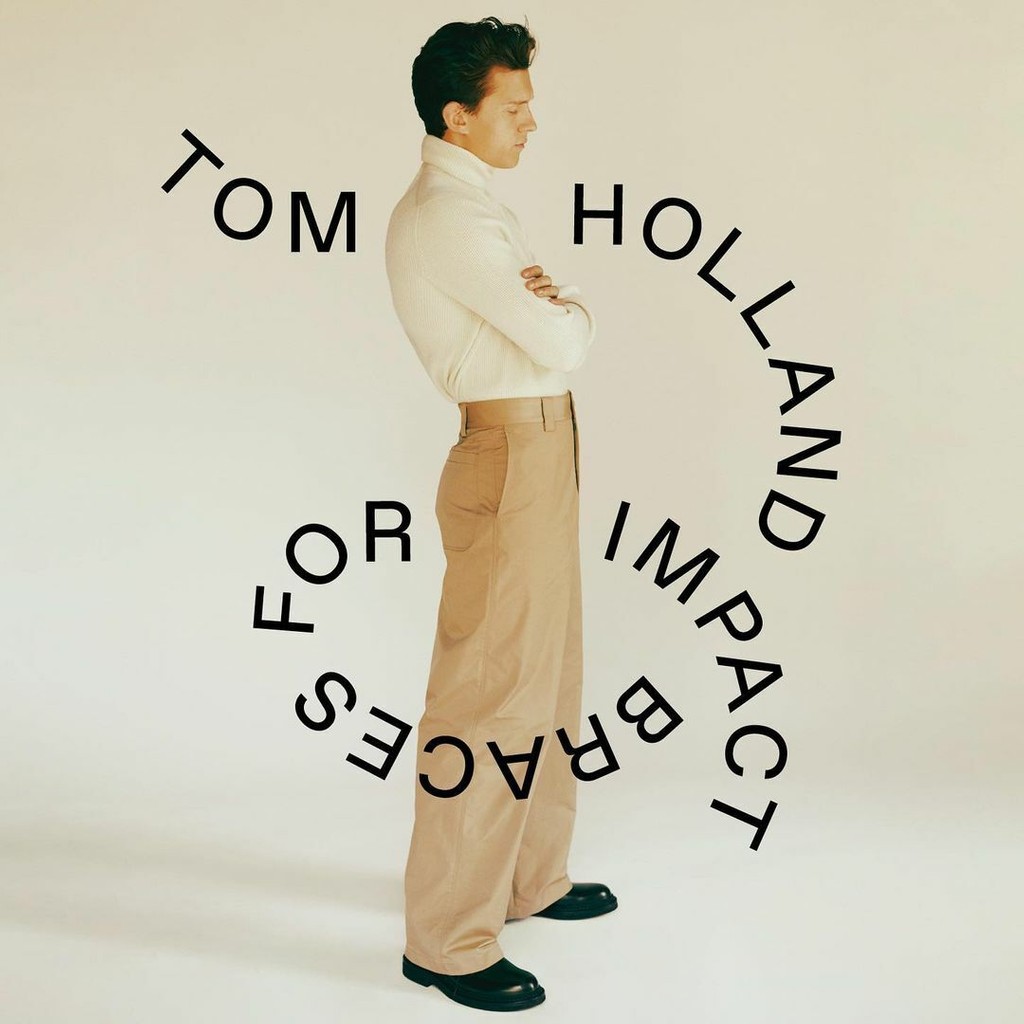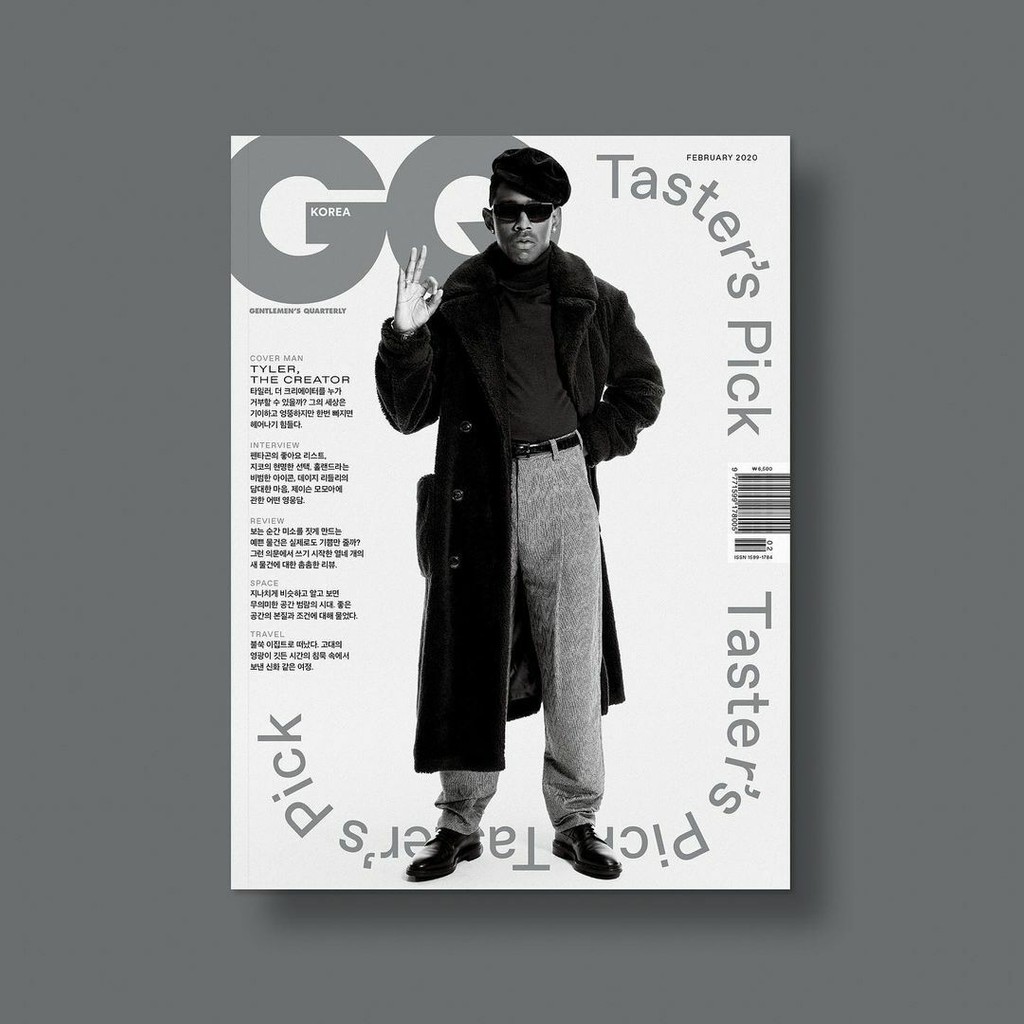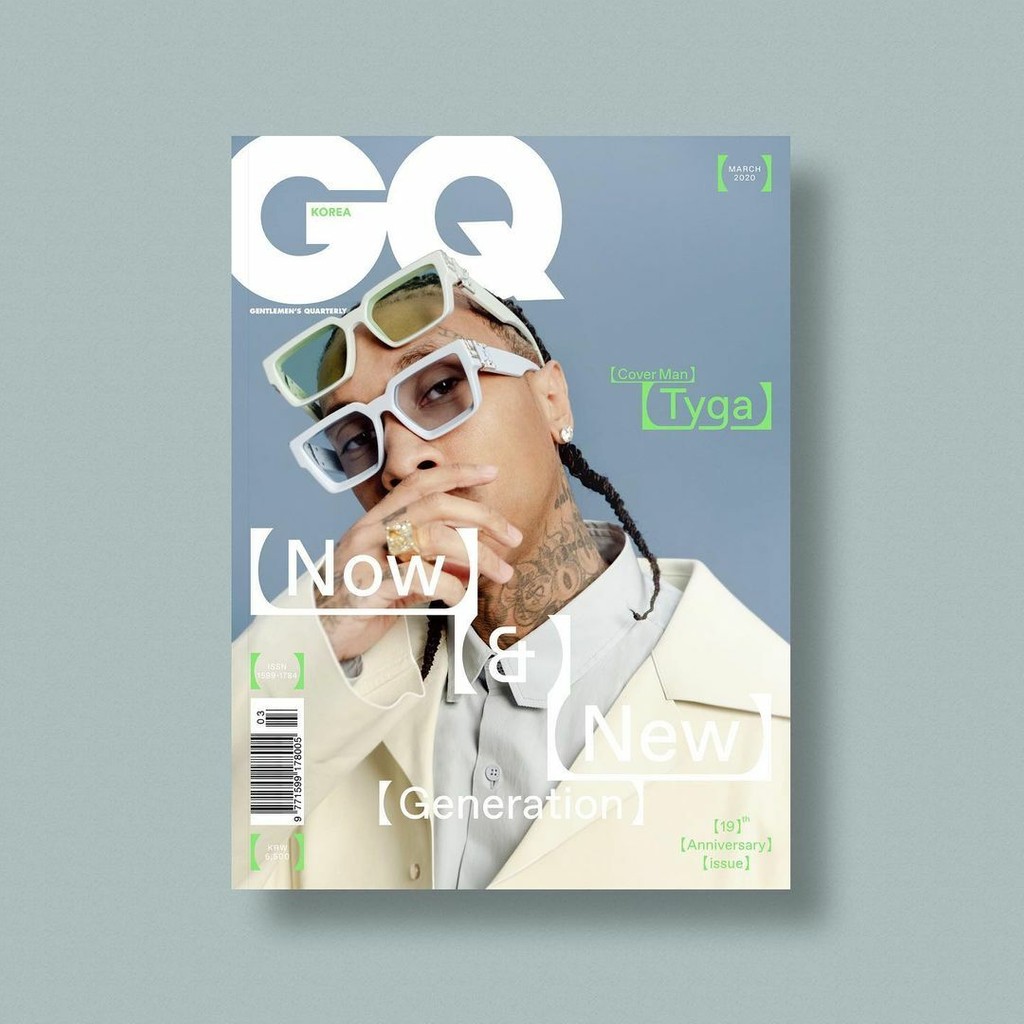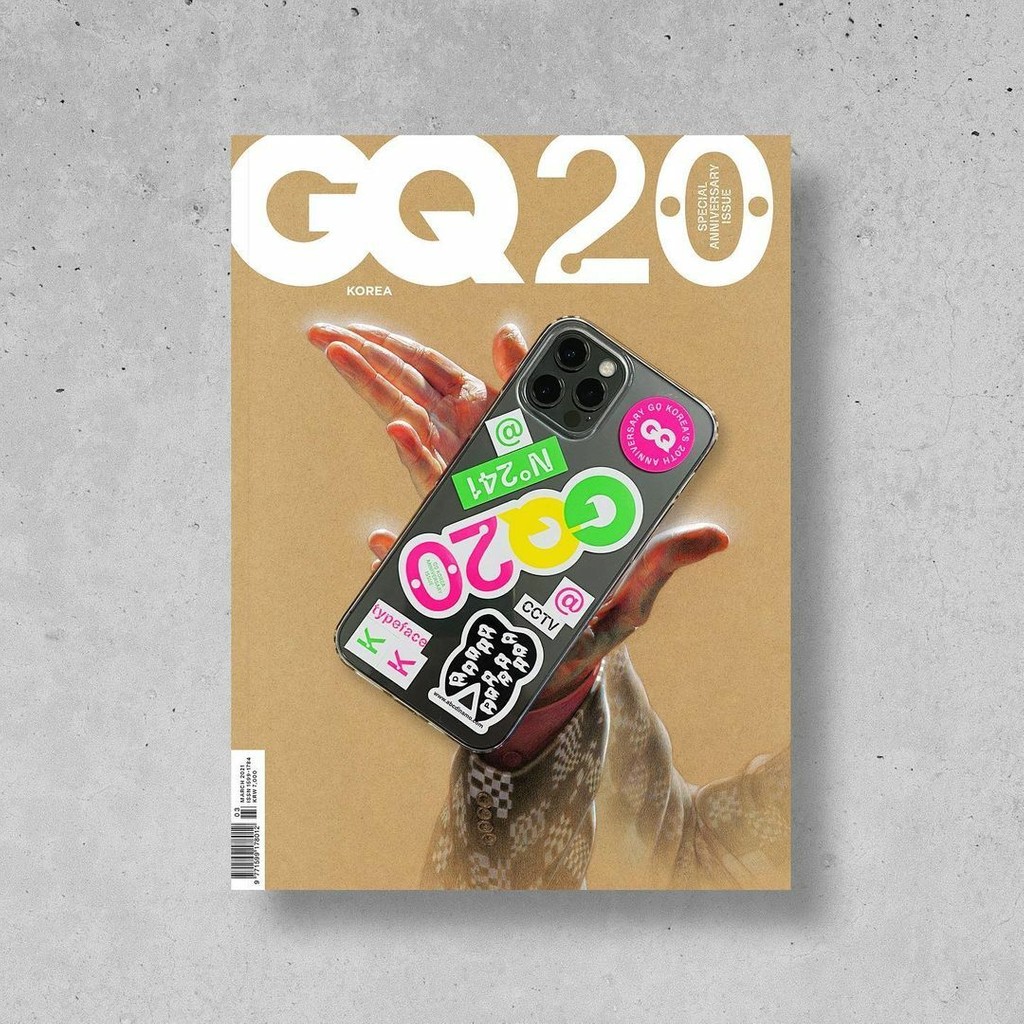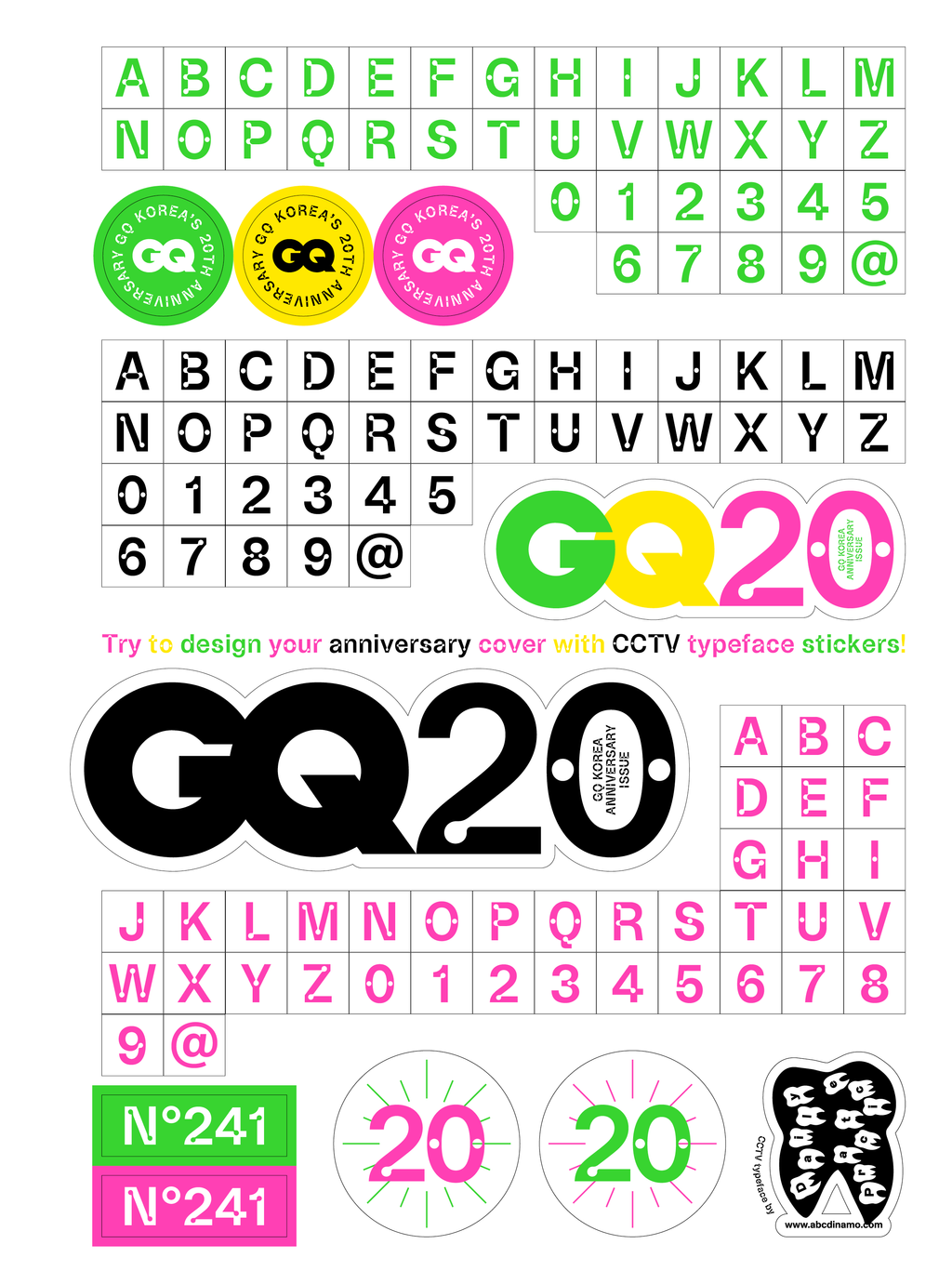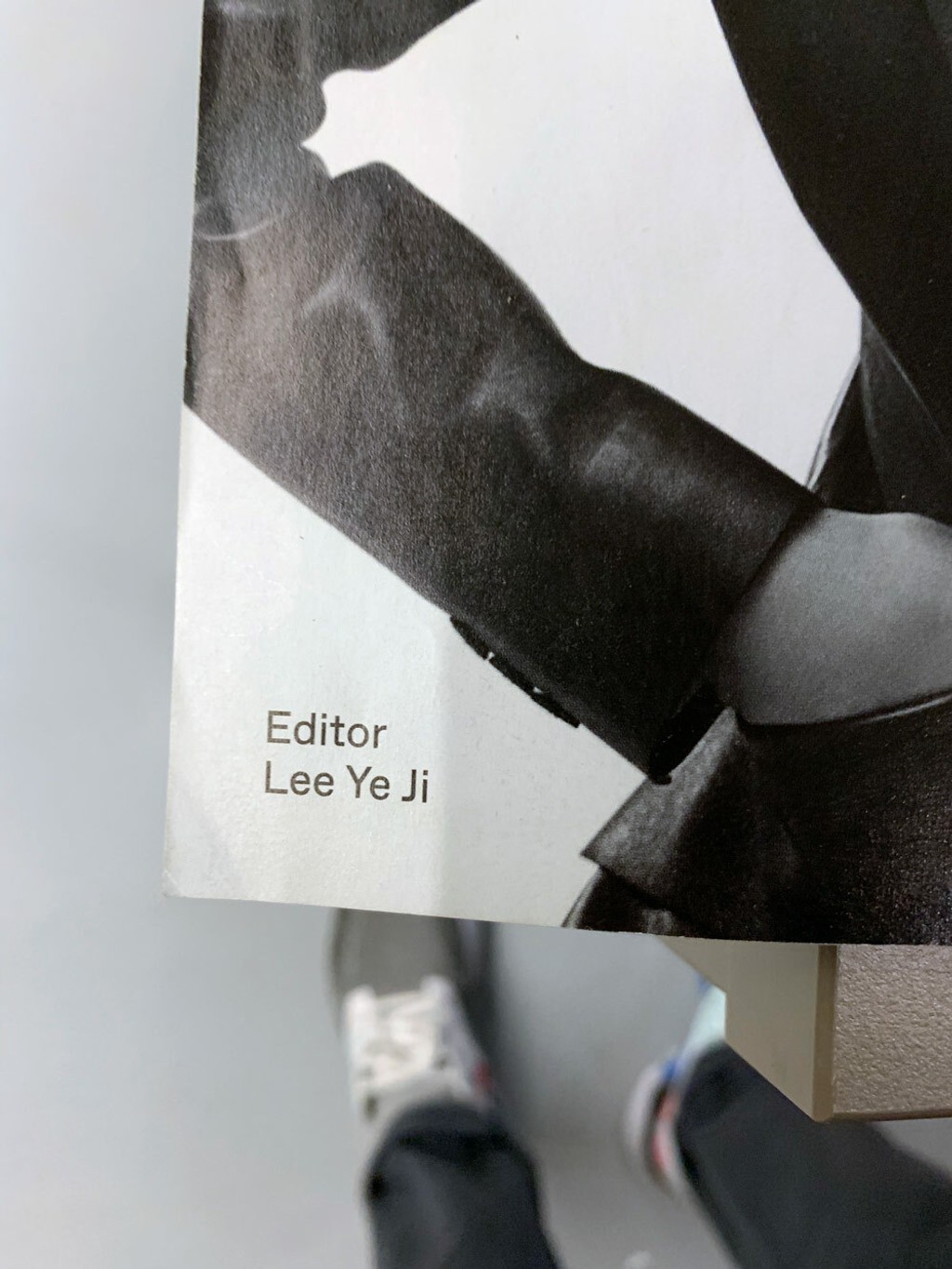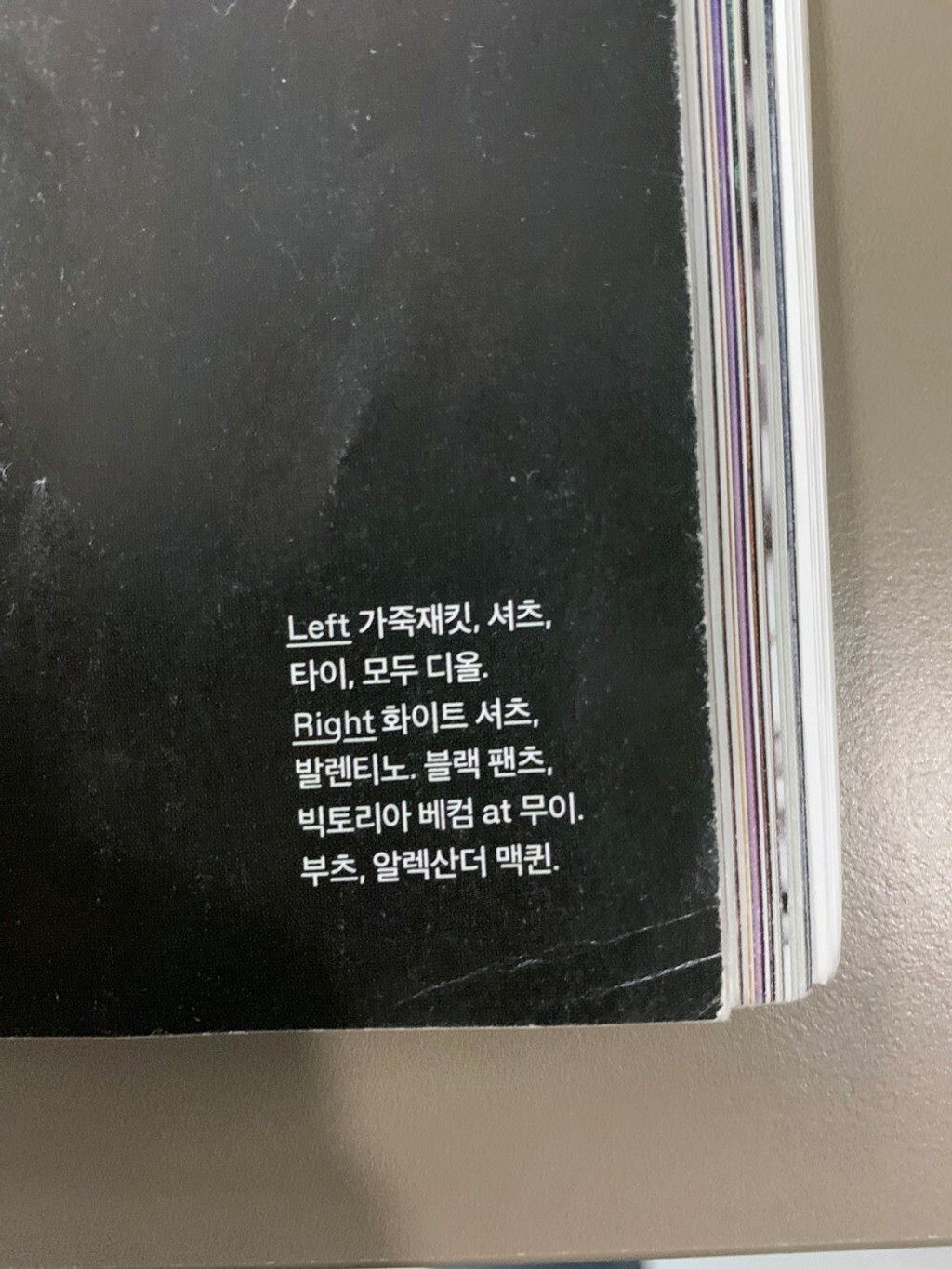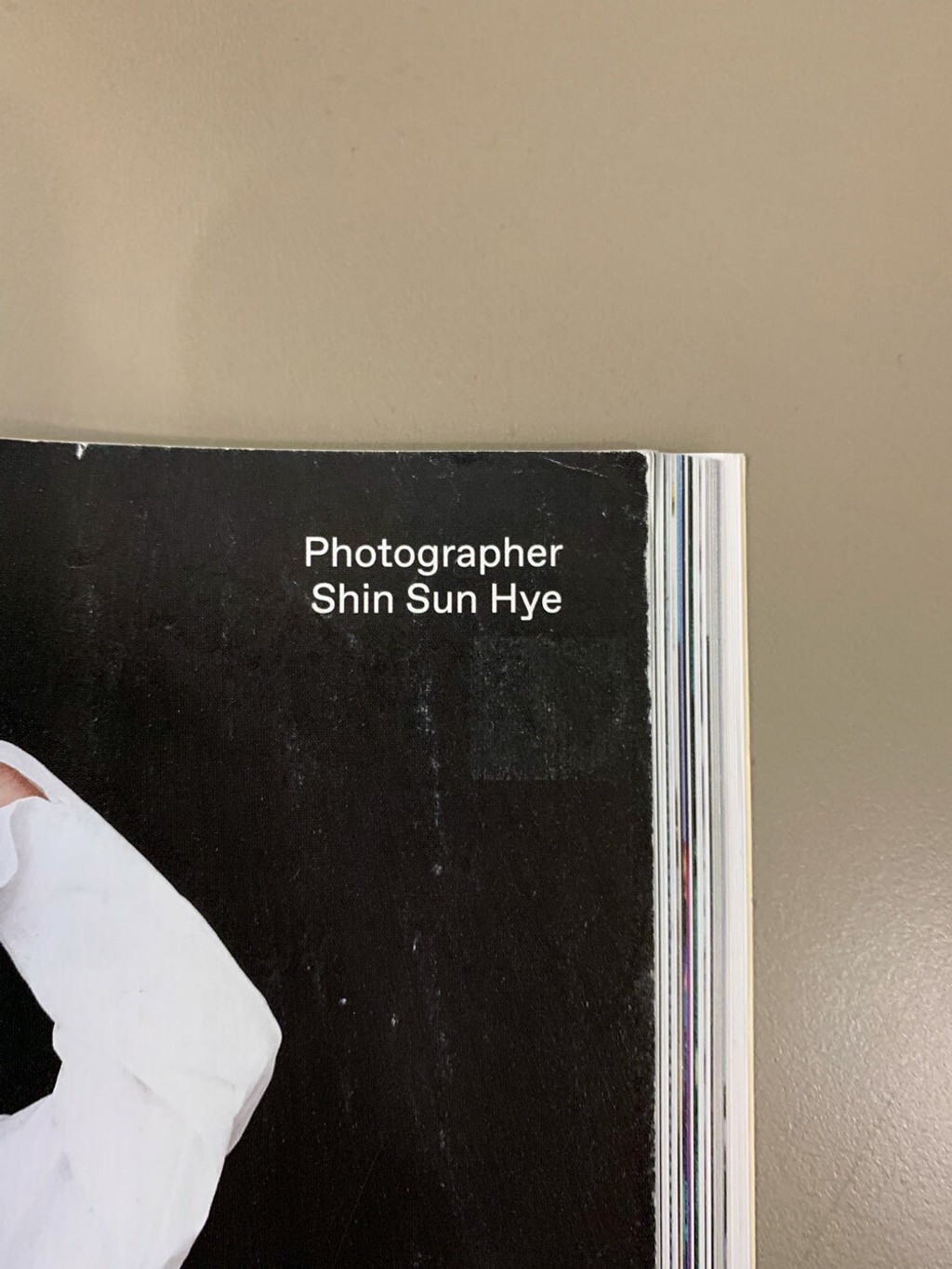
๋””๋‚˜๋ชจ x ๊น€๊ธฐ์—ด (์ง€ํ ์ฝ”๋ฆฌ์•„)
Dinamo x Kiyeol Kim at GQ Korea
์šฐ๋ฆฌ๋Š” ์ˆ˜๋…„๊ฐ„ ๊น€๊ธฐ์—ด๊ณผ ๋ฉ”์‹œ์ง€, โ€˜ํ•˜๋“œ์›จ์–ดโ€™ ๋ฐ ์‚ฌ์ „ ์ถœ์‹œ๋œ ๊ธ€๊ผด ํŒŒ์ผ์„ ๊ตํ™˜ํ•ด์™”๋‹ค. ์ง€ํ ์ฝ”๋ฆฌ์•„์—์„œ ๊น€๊ธฐ์—ด์€ ์ข…์ข… ํ•œ๊ธ€์˜ ํ•ต์‹ฌ๊ณผ ๊ทธ์— ๋Œ€์‘ํ•˜๋Š” ๋ผํ‹ด ํฐํŠธ๋ฅผ ๋ฉ‹์ง€๊ฒŒ ๊ฒฐํ•ฉํ•˜๋Š”๋ฐ, ์šฐ๋ฆฌ๋Š” ์ด ์•„ํŠธ ๋””๋ ‰ํ„ฐ๊ฐ€ ๋””์ž์ธ์— ์ ‘๊ทผํ•˜๋Š” ๋ฐฉ์‹์„ ํ•ญ์ƒ ํฅ๋ฏธ๋กญ๊ฒŒ ์ง€์ผœ๋ด ์™”๋‹ค. ๊ทธ ๋•์— ์šฐ๋ฆฌ๋Š” Camera, Maxi ๊ทธ๋ฆฌ๊ณ  Favorit๊ฐ€ ์ฒ˜์Œ์œผ๋กœ ์žก์ง€์— ๋“ฑ์žฅํ•˜๋Š” ๋ชจ์Šต์„ ์ฆ๊ฑฐ์šด ๋งˆ์Œ์œผ๋กœ ๋ณผ ์ˆ˜ ์žˆ์—ˆ๋‹ค. ์ตœ๊ทผ์—๋Š” ์ง€ํ ์ฝ”๋ฆฌ์•„๋„ ๋””๋‚˜๋ชจ์˜ ์ฒซ ํ•œ๊ธ€ ๊ธ€๊ผด์ธ ํŒŒ๋ณด๋ฆฌํŠธ ํ•œ๊ธ€(Favorit Hangul)์˜ ํŠน๋ณ„ํ•œ ์„œํฌํ„ฐ๊ฐ€ ๋˜์–ด์ฃผ์—ˆ๋‹ค.
February 2020 issue featuring Tasterโ€™s Pickโ€”Tyler the Creator, all typeset in Favorit Hangul.
March 2020 issue celebrating 19 years GQ Korea, and featuring Tyga and Favorit Hangul Lining.
Double spread from the September 2020 issue in Maxi.
2019๋…„ ํƒ€์ดํฌ์ž”์น˜์— ์ฐธ์—ฌํ–ˆ์„ ๋•Œ, ์šฐ๋ฆฌ๋Š” ๋“œ๋””์–ด ๊น€๊ธฐ์—ด๊ณผ ๊ฐœ์ธ์ ์œผ๋กœ ์†Œํ†ตํ•  ๊ธฐํšŒ๋ฅผ ์–ป๊ฒŒ ๋˜์—ˆ๋‹ค. ๊ทธ๊ณณ์—์„œ ์šฐ๋ฆฌ๋Š” ์œค๋ฏผ๊ตฌ๊ฐ€ ๋””์ž์ธํ•œ ํŒŒ๋ณด๋ฆฌํŠธ ํ•œ๊ธ€(Favorit Hangul)์˜ ์ถœ์‹œ๋ฅผ ๊ธฐ๋…ํ•˜์—ฌ ๊น€๋‚˜์š”, ๊ฐ•๋ฌธ์‹๊ณผ ํ•จ๊ป˜ ์ผ๋ จ์˜ โ€˜ํ•˜๋“œ์›จ์–ดโ€™ ์‹œ๋ฆฌ์ฆˆ๋ฅผ ์ œ์ž‘ํ•˜์˜€๋‹ค. ๊ทธ๋•Œ ์ดํ›„๋กœ ์šฐ๋ฆฌ๋Š” ์œค๋ฏผ๊ตฌ์™€ ํ•จ๊ป˜ (์—ฌ์ „ํžˆ ๋ฒ ์ผ์— ๊ฐ€๋ ค์ง„) ์šฐ๋ฆฌ์˜ ๋‘ ๋ฒˆ์งธ ํ•œ๊ธ€ ๊ธ€๊ผด ์ž‘์—…์— ๋ชฐ๋‘ํ•ด์˜ค๊ณ  ์žˆ๋‹ค(์ž์„ธํ•œ ๋‚ด์šฉ์€ ๊ณง). ๋ฐ”์ด ์Šคํฌ๋ฆฝํŠธ ํƒ€์ž… ๋””์ž์ธ์— ๊ด€ํ•ด ์œค๋ฏผ๊ตฌ๋Š” ์ด๋ ‡๊ฒŒ ๋งํ•œ๋‹ค. โ€œ์™„์ „ํžˆ ๋‹ค๋ฅธ ๋ณธ์„ฑ์„ ์ง€๋‹Œ ๋‘ ๊ฐœ์˜ ์Šคํฌ๋ฆฝํŠธ๋ฅผ ์กฐํ™”์‹œํ‚ค๋Š” ์ผ์€ ๊ฝค ๋„์ „์ ์ธ ์ž‘์—…์ด๋‹ค. ๊ฐ€๋ น ํ•œ๊ธ€์€ ๋ฒ ์ด์Šค๋ผ์ธ ๊ธฐ๋ฐ˜์˜ ์„œ์ฒด๊ฐ€ ์•„๋‹ˆ๊ธฐ ๋•Œ๋ฌธ์—, ๋ผํ‹ด๊ณผ ํ•œ๊ธ€ ๊ธ€๊ผด์„ ํ•œ ์ค„๋กœ ์ •๋ ฌํ•˜๋Š” ์ผ์€ ํ•ญ์ƒ ์ฒซ ๋ฒˆ์งธ ๋‹จ๊ณ„๋ผ ํ•  ์ˆ˜ ์žˆ๋‹ค. ํŒŒ๋ณด๋ฆฌํŠธ ํ•œ๊ธ€(Favorit Hangul)์˜ ๊ฒฝ์šฐ, ์„œ์ฒด ์ž์ฒด๋ฟ๋งŒ ์•„๋‹ˆ๋ผ ๋””๋‚˜๋ชจ์˜ ๋…ํŠนํ•˜๊ณ  ์žฌ๋ฏธ์žˆ์œผ๋ฉฐ ๋ฐœ๋ž„ํ•œ ๊ฐœ์„ฑ์„ ํ‘œํ˜„ํ•˜๋Š” ๊ฒƒ์ด ์ฃผ์š” ๊ณผ์ œ์˜€๋‹ค. ๊ฒฐ๊ตญ, ์•„์ฃผ ์ƒˆ๋กญ๊ณ  ์˜ˆ์ƒ์น˜ ๋ชปํ•œ ๊ฒฐ๊ณผ๊ฐ€ ๋‚˜์™”๋Š”๋ฐ, ํ•œํŽธ์œผ๋กœ๋Š” ์œ ๋จธ๋Ÿฌ์Šคํ•˜๋ฉด์„œ๋„ ๋‹ค๋ฅธ ํ•œํŽธ์œผ๋กœ๋Š” ๊ธฐ๋ณธ์— ์ถฉ์‹คํ•œ ๊ฒฐ๊ณผ๋ฌผ์ด๋ผ ํ•  ์ˆ˜ ์žˆ๋‹ค.โ€
๋‹ค๊ฐ€์˜ค๋Š” ๋””๋‚˜๋ชจ ํ•œ๊ธ€ ๊ธ€๊ผด ์ถœ์‹œ๋ฅผ ์•ž๋‘๊ณ (์šฐ๋ฆฌ๊ฐ€ ํ•ญ์ƒ ์–˜๊ธฐํ•ด์™”๊ธฐ ๋•Œ๋ฌธ์—), ์šฐ๋ฆฌ๋Š” ๊น€๊ธฐ์—ด์—๊ฒŒ ํ•œ๊ตญ์˜ ์„œ์ฒด ๋””์ž์ธ๊ณผ ์ง€ํ ์ฝ”๋ฆฌ์•„์— ๊ด€ํ•œ ๊ทธ์˜ ์ „๋ฐ˜์ ์ธ ๋น„์ „์„ ๋“ฃ๊ณ ์ž ๋ช‡ ๊ฐ€์ง€ ์งˆ๋ฌธ์„ ๋ณด๋‚ด๊ธฐ๋กœ ํ–ˆ๋‹ค. ์—ฌ๋Ÿฌ ์ฐจ๋ก€ ์‚ฐ๋ฐœ์ ์œผ๋กœ ์ง„ํ–‰๋œ ์ด๋ฉ”์ผ ์†Œํ†ต๋ฟ๋งŒ ์•„๋‹ˆ๋ผ, ์ง€๋‚œ ๋ช‡ ๋…„๊ฐ„ ๋””๋‚˜๋ชจ๋ฅผ ํ–ฅํ•œ ํŠน๋ณ„ํ•œ ์„œํฌํŠธ๋ฅผ ์•„๋ผ์ง€ ์•Š์€ ๊น€๊ธฐ์—ด์—๊ฒŒ ๊ฐ์‚ฌ์˜ ์ธ์‚ฌ๋ฅผ ํ‘œํ•œ๋‹ค!
First real-life-meet-up with Kiyeol on the corner of an unnamed Tteokbokki store in Seoul, October 2019.
Another spread from the September 2020 issue, a smart mix of Favorit and Maxi.
์ง€ํ ์ฝ”๋ฆฌ์•„ ๋งค๊ฑฐ์ง„์— ๊ด€ํ•œ ๋น„์ „์„ ๋“ค๋ ค์ฃผ์„ธ์š”.
์ €๋Š” ์ƒ์—… ์žก์ง€๋ฅผ ๋งŒ๋“ค๊ธฐ ๋•Œ๋ฌธ์— ๋‘ ๊ฐ€์ง€ ๋น„์ „์„ ๊ฐ€์ง€๊ณ  ์žˆ์Šต๋‹ˆ๋‹ค. ํ•˜๋‚˜๋Š” ๊ณต์ ์ธ ๋น„์ „, ๋‹ค๋ฅธ ํ•˜๋‚˜๋Š” ์‚ฌ์ ์ธ ๊ฒƒ์ด์ฃ . ์šฐ์„ , ์žก์ง€ ๋ฐœ๊ฐ„์„ ์œ ์ง€ํ•˜๊ณ  ํŒ๋งค๋ฅผ ์ฆ๊ฐ€์‹œํ‚ค๊ธฐ ์œ„ํ•ด, ์ถฉ๋ถ„ํ•œ ๊ด‘๊ณ  ์ˆ˜์ต์„ ์ฐฝ์ถœํ•ด์•ผ ํ•  ํ•„์š”์„ฑ ๋ฐ ๊ฒฝ์ œ์„ฑ์— ๋”ฐ๋ฅธ ๋น„์ „์„ ํ•˜๋‚˜ ๊ฐ€์ง€๊ณ  ์žˆ์Šต๋‹ˆ๋‹ค. ํ•˜์ง€๋งŒ ์ € ์—ญ์‹œ ์ œ๊ฐ€ ๊ฐœ์ธ์ ์œผ๋กœ ๋งŒ์กฑํ•  ๋งŒํ•œ ์žก์ง€๋ฅผ ๋งŒ๋“ค๊ณ  ์‹ถ์Šต๋‹ˆ๋‹ค. ๊ฐ€๋”์€ ์ ์ ˆํ•œ ํƒ€ํ˜‘์ ์„ ์ฐพ์•„ ๊ฒฐ๊ณผ๋ฌผ์— ๋งŒ์กฑํ•˜๊ธฐ๋„ ํ•˜์ง€๋งŒ, ๋‹ค๋ฅธ ํ•œํŽธ์œผ๋กœ๋Š” ์™„์ „ํžˆ ๋งŒ์กฑ์Šค๋Ÿฌ์šด ์žก์ง€๋ฅผ ๋งŒ๋“ค๊ณ  ์‹ถ๋‹ค๋Š” ๊ฐˆ๋ง ์—ญ์‹œ ํ•ญ์ƒ ๊ฐ€์ง€๊ณ  ์žˆ์Šต๋‹ˆ๋‹ค. ๊ด‘๊ณ ๊นŒ์ง€ ํฌํ•จํ•ด ๋ชจ๋“  ๋‚ด์šฉ์ด ํ•˜๋‚˜๋กœ ํ†ตํ•ฉ๋œ ์žก์ง€ ๋ง์ž…๋‹ˆ๋‹ค.
๋‹น์‹ ์€ ์˜ค๋žซ๋™์•ˆ ๋””๋‚˜๋ชจ์˜ ๊ธ€๊ผด์„ ์‚ฌ์šฉํ•ด ์™”์Šต๋‹ˆ๋‹ค. ์šฐ๋ฆฌ๊ฐ€ ๋Œ€ํ™”๋ฅผ ์‹œ์ž‘ํ•œ ๊ฒŒ ์–ธ์ œ์ธ์ง€, ๊ทธ๋ฆฌ๊ณ  ์šฐ๋ฆฌ ์„œ์ฒด ์ค‘ ๊ฐ€์žฅ ์ฒ˜์Œ ์‚ฌ์šฉํ•œ ๊ฒƒ์ด ๋ฌด์—‡์ธ์ง€ ๊ธฐ์–ตํ•˜์‹œ๋‚˜์š”?
5๋…„ ์ „์— ์†Œํ†ตํ•˜๊ธฐ ์‹œ์ž‘ํ–ˆ์ฃ . ๋‹น์‹œ ์ €๋Š” ์ง€ํ ์ฝ”๋ฆฌ์•„์—์„œ ์ผํ•œ ์ง€ 2๋…„ ์ฐจ์˜€๊ณ  ์ƒˆ๋กœ์šด ์•„์ด๋””์–ด๋ฅผ ํ–ฅํ•œ ๊ฐˆ์ฆ์ด ์žˆ๋˜ ๋•Œ์˜€์–ด์š”. ์ƒˆ๋กœ์šด ํŒ€์ด ๊พธ๋ ค์กŒ๊ณ , ์ƒˆ๋กœ์šด ๊ฒƒ์„ ์‹œ๋„ํ• , ๋‹ค๋ฅธ ์ข…๋ฅ˜์˜ ์žก์ง€๋ฅผ ๋งŒ๋“ค ํƒ€์ด๋ฐ์ด์—ˆ์Šต๋‹ˆ๋‹ค. ์ง€ํ ์ฝ”๋ฆฌ์•„ 16์ฃผ๋…„ ๊ธฐ๋… ๋ฆฌ๋””์ž์ธ์„ ์•ž๋‘๊ณ , ์ €๋Š” ๋””๋‚˜๋ชจ์˜ Prophet์„ ๋ฐœ๊ฒฌํ–ˆ๊ณ  ์ฃผ์ € ์—†์ด ๊ตฌ๋งคํ–ˆ์Šต๋‹ˆ๋‹ค. Prophet์€ ํ™•์‹คํžˆ ๋‹ค๋ฅธ ์„œ์ฒด์˜€์ง€์š”.
์ง€ํ ์ฝ”๋ฆฌ์•„์˜ 20์ฃผ๋…„ ๊ธฐ๋…ํ˜ธ๊ฐ€ ๋ฐฉ๊ธˆ ์ €ํฌ ์šฐํŽธํ•จ์— ๋„์ฐฉํ–ˆ์Šต๋‹ˆ๋‹ค. ๋‹ค์–‘ํ•œ ์š”์†Œ๋“ค๋กœ ์—„์ฒญ ๊ฐœ์„ฑ ์žˆ๋Š” ์žก์ง€๊ฐ€ ๋œ ๊ฒƒ ๊ฐ™์•„์š”. ๊ทธ๋ฆฌ๊ณ  ๊ณง ์ถœ์‹œ๋  ์ €ํฌ Camera๋ฅผ ์žก์ง€ ์ „๋ฐ˜์—์„œ ์ฐพ์•„๋ณผ ์ˆ˜ ์žˆ์–ด ๋„ˆ๋ฌด ์ข‹์Šต๋‹ˆ๋‹ค. ์ด๋ฒˆ ํ˜ธ๋ฅผ ์œ„ํ•ด Camera๋ฅผ ์„ ํƒํ•˜์‹  ์ด์œ ๊ฐ€ ๊ถ๊ธˆํ•ฉ๋‹ˆ๋‹ค.
Camera๋ฅผ ์‚ฌ์šฉํ•  ๊ธฐํšŒ๋ฅผ ์ฃผ์‹  ๋””๋‚˜๋ชจ์— ์ •๋ง ์ •๋ง ๊ฐ์‚ฌํ•ฉ๋‹ˆ๋‹ค! ์ €ํฌ๋Š” ๋ฃจ์ด๋น„ํ†ต๊ณผ์˜ ํ˜‘์—…์œผ๋กœ ์ด๋ฒˆ 20์ฃผ๋…„ ๊ธฐ๋… ์ปค๋ฒ„๋ฅผ ์ œ์ž‘ํ–ˆ์Šต๋‹ˆ๋‹ค. ๊ทธ๋Ÿฐ๋ฐ ์ฝ”๋กœ๋‚˜19 ๋•Œ๋ฌธ์— ํ•ด์™ธ ์ดฌ์˜์ด ๋ถˆ๊ฐ€๋Šฅํ•ด์ง€๋ฉด์„œ, ๋‹ค๋ฅธ ์ข…๋ฅ˜์˜ ์ปค๋ฒ„๊ฐ€ ํ•„์š”ํ•ด์กŒ์Šต๋‹ˆ๋‹ค.
์ €ํฌ 20์ฃผ๋…„ ๊ธฐ๋… 3๋ถ€์ž‘ ์ปค๋ฒ„๋Š” ๋ชจ๋ธ์ด๋‚˜ ์œ ๋ช…์ธ์‚ฌ๋ฅผ ์ „๋ฉด์— ๋‚ด์„ธ์šฐ๋˜ ๊ธฐ์กด์˜ ์ „ํ†ต ๋Œ€์‹  ์ž‘๊ฐ€ 3์ธ์˜ ๊ทธ๋ฆผ์œผ๋กœ ์žฅ์‹ํ–ˆ์Šต๋‹ˆ๋‹ค. ์ด๋ฒˆ ์•„ํŠธ ํ”„๋กœ์ ํŠธ์— Camera๊ฐ€ ๊ฐ€์ง„ ๋ผ์ดํŠธ ํŠธ๋žฉ ๊ตฌ๋ฉ๋“ค์ด ์•„์ฃผ ์ž˜ ์–ด์šธ๋ฆด ๊ฑฐ๋ผ ์ƒ๊ฐํ–ˆ๊ณ , ๊ฒฐ๊ตญ ๋งŽ์€ ์‚ฌ๋žŒ์ด ์ฆ๊ธธ ์ˆ˜ ์žˆ๋Š” ๋ฌด์–ธ๊ฐ€๋กœ ํƒ„์ƒํ–ˆ์ง€์š”. ์Šคํ”„๋ ˆ๋“œ ์ค‘์—๋Š” Camera ์ž์ฒด์˜ ๊ตฌ๋ฉ์—์„œ ๋„์ถœํ•œ ์›์„ ๋ชจํ‹ฐ๋ธŒ๋กœ ๋””์ž์ธํ•œ ํŽ˜์ด์ง€๋„ ์žˆ์Šต๋‹ˆ๋‹ค.
์ด๋ฒˆ ํ˜ธ์— ์ฒจ๋ถ€ํ•œ ์Šคํ‹ฐ์ปค๋ฅผ ํ†ตํ•ด Camera๊ฐ€ ๋„๋ฆฌ ์•Œ๋ ค์ง€๋Š” ๊ฑธ ๋ณด๋‹ˆ ๋„ˆ๋ฌด ์ข‹์•˜์Šต๋‹ˆ๋‹ค. ๊ทธ๋Ÿฐ ์•„์ด๋””์–ด๋Š” ์–ด๋–ป๊ฒŒ ๋‚˜์™”๋‚˜์š”?
์ž‘๊ฐ€๋“ค์˜ ๊ทธ๋ฆผ์œผ๋กœ ๊ตฌ์„ฑ๋œ ์„ธ ์ปค๋ฒ„์— ์ปค๋ฒ„ ๋ผ์ธ์„ ์ž…ํžˆ๋Š” ๊ฑด ์ ์ ˆํ•˜์ง€ ์•Š๋‹ค๊ณ  ํŒ๋‹จํ–ˆ์Šต๋‹ˆ๋‹ค. ๊ทธ ๋•Œ๋ฌธ์— ๋…์ž๊ฐ€ ์›ํ•œ๋‹ค๋ฉด ์•ŒํŒŒ๋ฒณ ์Šคํ‹ฐ์ปค๋ฅผ ์ด์šฉํ•ด ํ—ค๋“œ๋ผ์ธ์„ ๋งŒ๋“œ๋Š” ๋ฐฉ์‹์œผ๋กœ ์ง์ ‘ ์ปค๋ฒ„๋ฅผ ๊พธ๋ฐ€ ์ˆ˜ ์žˆ๊ฒŒ ํ•˜์ž๋Š” ์•„์ด๋””์–ด๊ฐ€ ๋– ์˜ฌ๋ž์Šต๋‹ˆ๋‹ค. ํŽธ์ง‘์žฅ๋‹˜๋„ ๊ธฐ๊บผ์ด ์ด ์ œ์•ˆ์„ ๋ฐ›์•„์ฃผ์…จ์ฃ . ์ด๋ฒˆ ํ˜ธ๊ฐ€ ์ถœ๊ฐ„๋œ ๋’ค์— ์ €ํฌ ์ฃผ๋ณ€์ธ๋“ค์ด ์ž์‹ ์˜ ์Šค๋งˆํŠธํฐ์ด๋‚˜ ๋…ธํŠธ๋ถ์— ์ด ์Šคํ‹ฐ์ปค๋ฅผ ๋ถ™์ด๊ธฐ ์‹œ์ž‘ํ•˜๋Š” ๊ฑธ ๋ฐœ๊ฒฌํ–ˆ์–ด์š”. ๋””๋‚˜๋ชจ์˜ ์ด๋นจ ์Šคํ‹ฐ์ปค๋„ ์ธ๊ธฐ๊ฐ€ ๋งŽ์•˜์Šต๋‹ˆ๋‹ค!
๋„ˆ๋ฌด ๊ธฐ์œ ์†Œ์‹์ด์—์š”! ๋‹น์‹ ์€ ํŒจ์…˜ ์Šคํ”„๋ ˆ๋“œ์—๋„ Maxi๋ฅผ ์‚ฌ์šฉํ•ด์™”์Šต๋‹ˆ๋‹ค. ํŒจ์…˜์ด๋ผ๋Š” ๋งฅ๋ฝ์—์„œ Maxi๋ฅผ ์‚ฌ์šฉํ•  ๋•Œ๋Š” ์–ด๋–ค ์ ์ด ์ข‹์•˜๋‚˜์š”?
๋””๋‚˜๋ชจ๊ฐ€ ๋กœ๊ณ ์— Maxi๋ฅผ ์–ด๋–ป๊ฒŒ ์‚ฌ์šฉํ•˜๋Š”์ง€ ๋ณด๊ณ  ๋‚˜์„œ ์ €๋„ Maxi๋ฅผ ์‚ฌ์šฉํ•˜๊ณ  ์‹ถ์—ˆ์ง€๋งŒ ๋งˆ๋•…ํ•œ ํ”„๋กœ์ ํŠธ๋ฅผ ์ฐพ์ง€ ๋ชปํ–ˆ์Šต๋‹ˆ๋‹ค. ๊ทธ๋Ÿฌ๋˜ ์ค‘ 2020๋…„ 9์›”ํ˜ธ์— ๋ฐœํ‘œ๋  ์˜ˆ์ •์ด์—ˆ๋˜ ๋ฐœ๋ Œ์‹œ์•„๊ฐ€ ์บ ํŽ˜์ธ์˜ ์‚ฌ์ง„๋“ค์„ ๋ณด๊ณ , ๋“œ๋””์–ด Maxi๋ฅผ ์‚ฌ์šฉํ•  ์ˆ˜ ์žˆ๊ฒŒ ๋˜์—ˆ์Šต๋‹ˆ๋‹ค. Maxi๋Š” ๋งˆ์น˜ ํ•˜๋‚˜์˜ ๊ธฐ๊ณ„ ๋ถ€ํ’ˆ์ฒ˜๋Ÿผ ๋ณด์ด๊ธฐ ๋•Œ๋ฌธ์— ๋‹น์‹œ ์ดฌ์˜ ํ†ค์— ์ž˜ ์–ด์šธ๋ ธ๊ณ , ๊ทธ๋ž˜์„œ ์ด๊ฑธ ์‚ฌ์šฉํ•˜๋ฉด ์ข‹๊ฒ ๋‹ค๊ณ  ์ƒ๊ฐํ–ˆ์Šต๋‹ˆ๋‹ค. ๊ทธ ์Šคํ”„๋ ˆ๋“œ๋Š” Maxi๋งŒ์œผ๋กœ๋„ ํ›Œ๋ฅญํ–ˆ์ง€๋งŒ, ๊ทธ ํ˜ธ์˜ ๋‹ค๋ฅธ ์Šคํ”„๋ ˆ๋“œ์™€ ๋™๊ธฐํ™”ํ•˜๊ธฐ ์œ„ํ•ด ์ €ํฌ๋Š” Maxi์™€ Favorit๋ฅผ ์„ž์–ด ์‚ฌ์šฉํ–ˆ์Šต๋‹ˆ๋‹ค. Maxi๋Š” ํ•œ ์ž ํ•œ ์ž์— ๋งค๋ ฅ๊ณผ ํ†ต์ผ์„ฑ์ด ์žˆ๋Š”, ๊ท€์—ฌ์šฐ๋ฉด์„œ ๋ฉ‹์ง„ ์„œ์ฒด์ž…๋‹ˆ๋‹ค. ๊ทธ ๋•Œ๋ฌธ์— Maxi๋Š” ๋ฏน์Šค๋งค์น˜๋ฅผ ํ•  ์ˆ˜ ์žˆ๋Š” ๊ฐ€๋Šฅ์„ฑ์ด ๋ฌดํ•œํ•˜๋‹ค๊ณ  ์ƒ๊ฐํ•ฉ๋‹ˆ๋‹ค.
๋‹น์‹ ์€ ์‹ค์ œ๋กœ ์šฐ๋ฆฌ ํŒŒ๋ณด๋ฆฌํŠธ ํ•œ๊ธ€(Favorit Hangul)์˜ ์ฒซ ํ…Œ์Šคํ„ฐ์ด์ž ํ”ผ๋“œ๋ฐฑ์„ ์ค€ ์‚ฌ๋žŒ์ž…๋‹ˆ๋‹ค. ์–ด๋• ์Šต๋‹ˆ๊นŒ?
ํŒŒ๋ณด๋ฆฌํŠธ ํ•œ๊ธ€(Favorit Hangul)์„ ์‚ฌ์šฉํ•˜์ž ๊ธฐ๋ณธ์ ์œผ๋กœ ์‹œ๊ฐ„ ์†Œ๋ชจ๊ฐ€ ๋งŽ์•˜๋˜ ๋ฌธ์ œ๋“ค์ด ํ•ด๊ฒฐ๋˜์—ˆ์Šต๋‹ˆ๋‹ค. ํ•œ๊ธ€ ๊ธ€๊ผด์— ๋ผํ‹ด ๋ฌธ์ž๊ฐ€ ํฌํ•จ๋˜๋ฉด, ๋Œ€๊ฒŒ ๊ทธ ๋ผํ‹ด ๋ฌธ์ž๋Š” ์šฐ๋ฆฌ๊ฐ€ ๋ชฉํ‘œ๋กœ ํ•˜๋Š” ๋””์ž์ธ์— ๋งž์•„๋–จ์–ด์ง€์ง€ ์•Š์Šต๋‹ˆ๋‹ค. ๊ทธ๋ž˜์„œ ์ด๋Ÿฐ ๊ฒฝ์šฐ์— ์šฐ๋ฆฌ๋Š” ๋ณดํ†ต ๋‘ ๊ฐœ์˜ ๊ธ€๊ผด์„ ์ง์ ‘ ๋งž์ถฐ์„œ ์‚ฌ์šฉํ•ด์•ผ ํ•ฉ๋‹ˆ๋‹ค.
Favorit๋ฅผ ์‚ฌ์šฉํ•˜๊ธฐ ์ „์—๋Š” ํ•œ๊ธ€๊ณผ ๋ผํ‹ด ์„œ์ฒด๋ฅผ ์„ž์–ด ๋ณธ๋ฌธ์„ ์กฐํŒํ–ˆ์Šต๋‹ˆ๋‹ค. ๊ทธ๋Ÿฌ๋‚˜ ์—ฌ๊ธฐ์—๋Š” ๋ช‡ ๊ฐ€์ง€ ๋ฌธ์ œ๊ฐ€ ์žˆ์—ˆ์Šต๋‹ˆ๋‹ค. ์˜ˆ๋ฅผ ๋“ค์–ด, ํ•œ๊ตญ์–ด์™€ ๋ผํ‹ด ์„œ์ฒด๋ฅผ ํ•จ๊ป˜ ์‚ฌ์šฉํ•  ๋•Œ๋Š” ๋‘ ์„œ์ฒด์˜ ๊ตต๊ธฐ์™€ ํฌ๊ธฐ๊ฐ€ ๋งž๋„๋ก ์ˆ˜๋งŽ์€ ๋””ํ…Œ์ผ ์กฐ์ •์ด ํ•„์š”ํ•ฉ๋‹ˆ๋‹ค.
์ด๋Ÿฐ ์‹์œผ๋กœ ๋‘ ๊ธ€๊ผด์„ ์กฐ์œจํ•œ ํ…์ŠคํŠธ๋ฅผ ์ฝ์„ ๋•Œ๋ฉด, ์ข…์ข… ๋ฏธ์„ธํ•œ ์‹œ๊ฐ์  ๋Š๊น€์„ ๋А๋ผ๊ณค ํ–ˆ์Šต๋‹ˆ๋‹ค. ๊ทธ๋ฟ๋งŒ ์•„๋‹ˆ๋ผ ์ด๋Ÿฐ ๋ฐฉ์‹์€ ์ธ๋””์ž์ธ ์Šคํƒ€์ผ ๋ฆฌ์ŠคํŠธ๋ฅผ ๋งŒ๋“œ๋Š” ๋ฐ ์ˆ˜๋งŽ์€ ์‹œ๊ฐ„๊ณผ ๋…ธ๋ ฅ์„ ์š”๊ตฌํ•˜๊ณ , ๋˜ํ•œ ๋งŽ์€ ์–‘์˜ ๊ทธ๋ ™ ์‚ฌ์šฉ ๋•Œ๋ฌธ์— ๋ฌธ์„œ๋ฅผ ์˜ฎ๊ธฐ๋Š” ๊ฒƒ๋„ ์˜ค๋ž˜ ๊ฑธ๋ฆฝ๋‹ˆ๋‹ค. ๊ทธ๋Ÿฐ๋ฐ Favorit๋ฅผ ์‚ฌ์šฉํ•œ ๋’ค๋กœ๋Š” ํ•œ๊ตญ์–ด์™€ ๋ผํ‹ด ๋ฌธ์ž ๋ชจ๋‘์—์„œ ์กฐํ™”๋กญ๊ณ  ๋งค๋ˆํ•œ ์„ค์ •์ด ๊ฐ€๋Šฅํ•ด์กŒ์Šต๋‹ˆ๋‹ค. ๋™์‹œ์— ๋ฌธ์„œ๋ฅผ ๋‹ค๋ฃจ๋Š” ์ผ๋„ ํ›จ์”ฌ ์‰ฌ์›Œ์กŒ์Šต๋‹ˆ๋‹ค. ์ด์ œ ๋ณธ๋ฌธ์—์„œ ๊ณ ๋”•์ฒด๋ฅผ ์‚ฌ์šฉํ•  ์ผ์ด ์ƒ๊ธฐ๋ฉด ์ €ํฌ๋Š” Favorit๋ฅผ ํ•ญ์ƒ ์šฐ์„ ์ˆœ์œ„๋กœ ๊ณ ๋ คํ•ฉ๋‹ˆ๋‹ค.
๋” ์ผ๋ฐ˜์ ์ธ ์ธก๋ฉด์—์„œ, ํ˜„์žฌ ํ•œ๊ธ€ ์„œ์ฒด ์„ธ๊ณ„์˜ ๋ฐœ์ „ ์ƒํ™ฉ์€ ์–ด๋–ค์ง€ ๋‹น์‹ ์˜ ์‹œ๊ฐ์—์„œ ๋“ฃ๊ณ  ์‹ถ์Šต๋‹ˆ๋‹ค. ๊ทธ๋ฆฌ๊ณ  ์ด์™€ ๊ด€๋ จํ•ด ๋” ๊ธฐ๋Œ€ํ•˜์‹œ๋Š” ๋ฐ”๊ฐ€ ์žˆ๋‚˜์š”?
ํ•œ๊ธ€ ์ดํƒค๋ฆญ๊ณผ ํ•„๊ธฐ์ฒด๊ฐ€ ์กฐ๊ธˆ ๋” ๋ฐœ์ „ํ•œ๋‹ค๋ฉด ์ข‹์„ ๊ฒƒ ๊ฐ™์Šต๋‹ˆ๋‹ค. ํ•˜์ง€๋งŒ ํ•œ๊ธ€์€ ๋ผํ‹ด ์„œ์ฒด์™€ ๋น„๊ตํ–ˆ์„ ๋•Œ ๊ตฌ์กฐ์ ์ธ ์ฐจ์ด๊ฐ€ ํฌ๊ณ  ๊ธ€์ž ์ˆ˜๋„ ํ›จ์”ฌ ๋งŽ๊ธฐ ๋•Œ๋ฌธ์—, ์ด๋Š” ํ•œ๊ตญ์–ด ์„œ์ฒด ๋””์ž์ด๋„ˆ๋“ค์—๊ฒŒ ๋ชน์‹œ ์–ด๋ ค์šด ์ž‘์—…์ด๋ผ๊ณ  ์ƒ๊ฐํ•ฉ๋‹ˆ๋‹ค.
์ข€ ๋” ์ผ๋ฐ˜์ ์ธ ๊ด€์ ์—์„œ ๋ณด์ž๋ฉด, ํ˜„์žฌ ํ•œ๊ธ€ ํ™œ์ž ๋””์ž์ธ์„ ํ–ฅํ•œ ๊ด€์‹ฌ์€ ๊ทธ ์–ด๋А ๋•Œ๋ณด๋‹ค ๋†’์„ ๋ฟ๋งŒ ์•„๋‹ˆ๋ผ, ๋” ๋งŽ์€ ๋””์ž์ด๋„ˆ๋“ค์ด ์ƒˆ๋กœ์šด ์„œ์ฒด๋ฅผ ๊ฐœ๋ฐœํ•˜๊ณ  ์žˆ์Šต๋‹ˆ๋‹ค. ๊ทธ๋ž˜์„œ ์ด์ œ๋Š” ๋” ๋‹ค์–‘ํ•œ ํ•œ๊ธ€ ์„œ์ฒด์™€ ๋ ˆํ„ฐ๋ง์ด ์ƒ๊ธฐ๊ณ  ์žˆ๊ณ , ๋‚˜์•„๊ฐ€ ํ•œ๊ธ€๊ณผ ๋ผํ‹ด ๋ฌธ์ž๋ฅผ ๊ฒฐํ•ฉํ•˜๋Š” ๋ฐฉ๋ฒ•์— ๊ด€ํ•œ ์—ฐ๊ตฌ๋„ ๋งŽ์ด ์ง„ํ–‰๋˜๊ณ  ์žˆ์Šต๋‹ˆ๋‹ค. ๋˜ํ•œ ํ•œ๊ธ€์ฒ˜๋Ÿผ ๊ธ€์ž ์ˆ˜๊ฐ€ ๋งŽ์€ ์•ŒํŒŒ๋ฒณ์— ์œ ์šฉํ•œ ๊ฐ€๋ณ€ ๊ธ€๊ผด์„ ํ–ฅํ•œ ๊ด€์‹ฌ ์—ญ์‹œ ํฌ๊ณ ์š”!
Kiyeol before and after
When combining Hangul and Latin fonts, a lot of effort goes into synchronizing the visual balanceโ€”a laborious task and valuable time that is saved when using multi-script typefaces.
Dinamo J15 ABC Favorit Hangul 01
Family overview of Favorit Hangul and Favorit Hangul Lining, designed with the one and only Mingoo Yoon โค๏ธ
Hangul Website
Dinamo x Kiyeol Kim at GQ Korea
Weโ€™ve been exchanging messages, Hardware, and pre-released font files with Kiyeol Kim for a number of years now. Weโ€™re always excited to see how the art director approaches his design for GQ Korea, where he often combines a Hangul core with surprising Latin counterparts. Itโ€™s in this way that we first got to enjoy seeing our own Camera, Maxi, and Favorit making appearances across the magazine, and lately, GQ Korea has also been a special supporter of our first Hangul release, Favorit Hangul.
Dinamo Typefaces GQ Mock Up 2020 09 3000 6
Another spread from the September 2020 issue.
GQ Korea Gravity
Newly arrived to our Swiss letterbox: The August 2021 issue in a random width-mix of Robert Janesโ€™ Gravity typeface.
Dinamo Typefaces 170 181 GQ Well Zero
And yet another double spread from the September 2020 issue.
We finally got the chance to connect with Kiyeol personally in 2019, when we participated in Typojanchi and produced a series of Hardware with Nayo Kim and Moonsick Gang to celebrate the launch of Favorit Hangul, designed with Mingoo Yoon. Since then, weโ€™ve been working hard with Mingoo on our second, still secret Hangul release (more on this soon). As Mingoo says of bi-scriptual type design: โ€œItโ€™s quite challenging to harmonise two scripts with totally different natures. For example, Hangul is not a baseline-based script, so aligning the line of the Latin and Hangul scripts is always the first step. For Favorit Hangul, the main challenge was to express the unique, fun, and cheerful character of the font and also Dinamo: The result looks very new and unexpectedโ€”itโ€™s humorous but also faithful to the basics.โ€
In anticipation of our upcoming Hangul releaseโ€”and because we've always been talkingโ€”we decided to send Kiyeol some questions about type design in South Korea as well as his vision for GQ Korea more broadly. Thank you to Kiyeol for this ongoing, sporadic email exchange and for your special support of Dinamo over the last years! <3 <3 <3
71523623 563378631135177 8504737155199416085 n
Favorit for Tom Hollandโ€™s impact appearance in the May 2020 issue.
IMG 3691
Favorit details in a heavily consulted GQ Korea copy found at the wonderful Magazine Club bookshop.
IMG 3692
IMG 3690
Tell us about your time working for GQ Korea and your vision for the magazine.
I make a commercial magazine and therefore have two visions for it, one public and one private. First, I have a vision determined by economics and the necessity of generating enough advertising revenue to keep the magazine circulating and sales increasing. But then I also want to create a magazine that is personally satisfying. Sometimes I find an appropriate compromise and am satisfied with the results, but I always have the desire to create a magazine that is absolutely satisfyingโ€”unifying all the content of the magazine together, including its advertisements.
You're a long time user of our fonts. Do you remember when we started talking together and what typeface of ours you first used?
We started talking five years ago. Two years had passed since I began working at GQ Korea, and I had a thirst for new ideas. There was a new team, and it was time to try new things and make a different kind of magazine. Ahead of GQ Koreaโ€™s 16th anniversary redesign, I found Dinamo's Prophet and I bought it without hesitation. Prophet was a distinctly different typeface.
GQ Korea's 20th anniversary issue just arrived in our letterbox. It has such character, with all the different inserts, and it's exciting to see our upcoming ABC Camera explored throughout the pages so extensively. Why did you choose Camera for this issue?
I'm very, very grateful to Dinamo for giving me the opportunity to use Camera! We made the 20th anniversary cover in collaboration with Louis Vuitton. However due to Covid-19, shooting abroad wasn't possible, and so a different kind of cover was needed.
Our 20th anniversary trilogy of covers featured paintings by three artists, rather than our existing tradition of featuring models or celebrities on the front. I thought that the light trap holes of Camera would match nicely with this art project. It came together into something that many people have enjoyed. Among the spreads, there are also pages designed with the motif of a circle that emerged from Camera's own holes.
It's been crazy for us to see how Camera has spread so much with the sticker sheets you included in the issue. How did that idea actually come about?
I decided that it was not appropriate to put a cover line on three covers featuring drawings by artists, so I came up with the idea that the readers themselves could decorate the cover with headlines if they wanted to using alphabetical stickers. The editor-in-chief happily accepted this proposal. We noticed people around us started putting stickers on their smartphones or laptops when the issue was released. Your tooth sticker has also been very popular!
Thatโ€™s amazing to hear! Youโ€™ve also been using Maxi for some of your fashion spreads. What have you enjoyed about Maxi in these fashion contexts?
From the moment I saw how you used Maxi in your logo, I thought I would like to use it too, but I couldn't find a suitable project. I was finally able to use it when after I saw photographs of the Balenciaga campaign that were going to be published in the September 2020 issue. I thought it would be great to use Maxi because it looks like single machine parts, which suited the tone of the shoot. The spreads were great with Maxi on its own, but to sync it with other spreads in the issue, we mixed Maxi and Favorit together. Maxi is a cute and cool typeface where each character has a sense of charm and unityโ€”I think there is an infinite possibility to mix and match with it.
You've actually been one of our very first Favorit Hangul testers and feedbackers. How's that going?
A lot of time-consuming challenges have basically been solved by using Favorit Hangul. When Latin characters are included in Korea fonts, usually the Latin characters donโ€™t work for the design weโ€™re aiming for. So in this case, weโ€™ll usually have to pair two fonts together ourselves.
Before using Favorit, we were typesetting body copy by mixing Hangul and Latin typefaces together. There were some issues with this: For instance, when using Korean and Latin typefaces, you have to make lots of detailed adjustments in the weights and sizes so that they fit together.
When I read the text after we'd adjusted two fonts like this, I often felt the subtle visual interruption. Plus it took a lot of time and effort to create an InDesign style list, and moving the document was slow due to the use of many greps. With Favorit though, itโ€™s now possible to set up harmonious and smooth copy in both Korea and Latin. And handling the document is far easier. Now, when weโ€™re using Gothic typefaces for body copy, Favorit is always our first consideration.
More generally, weโ€™d love to know from your perspective: What are the current developments in the Hangul type world like at the moment? And is there something you wish you'd see more of?
It would be nice if the development of Hangul italics and scripts progressed a little more. However, I think it's a very difficult task for Korean typeface designers, as Hangul as significant structural differences from Latin typefaces and a much larger number of characters.
More generally, interest in Hangul type design is higher than itโ€™s ever been, with more and more designers creating new typefaces. So now, more diverse Hangul typefaces and lettering are appearing and thereโ€™s a lot of research going into how to pair Hangul and Latin characters together. Thereโ€™s also a great interest in variable fonts, which are very useful for alphabets with a large number of characters like Hangul!
156282891 1366594863695382 2743155122141807125 n 1
Cover star Kim Jung Gi with his still prestine Anniversary Issue.
20th Sticker
The anniversary sticker set featuring our own Camera.
ABC Favorit Hangul: Mingoo Yoon with Dinamo
ABC Favorit: Dinamo (Johannes Breyer & Fabian Harb)
ABC Maxi: Dinamo (Johannes Breyer & Fabian Harb with Andree Paat)
ABC Camera: Dinamo (Johannes Breyer, Fabian Harb, Robert Janes) with Sascha Bente
ABC Prophet: Dinamo (Johannes Breyer & Fabian Harb with Erkin Karamemet)